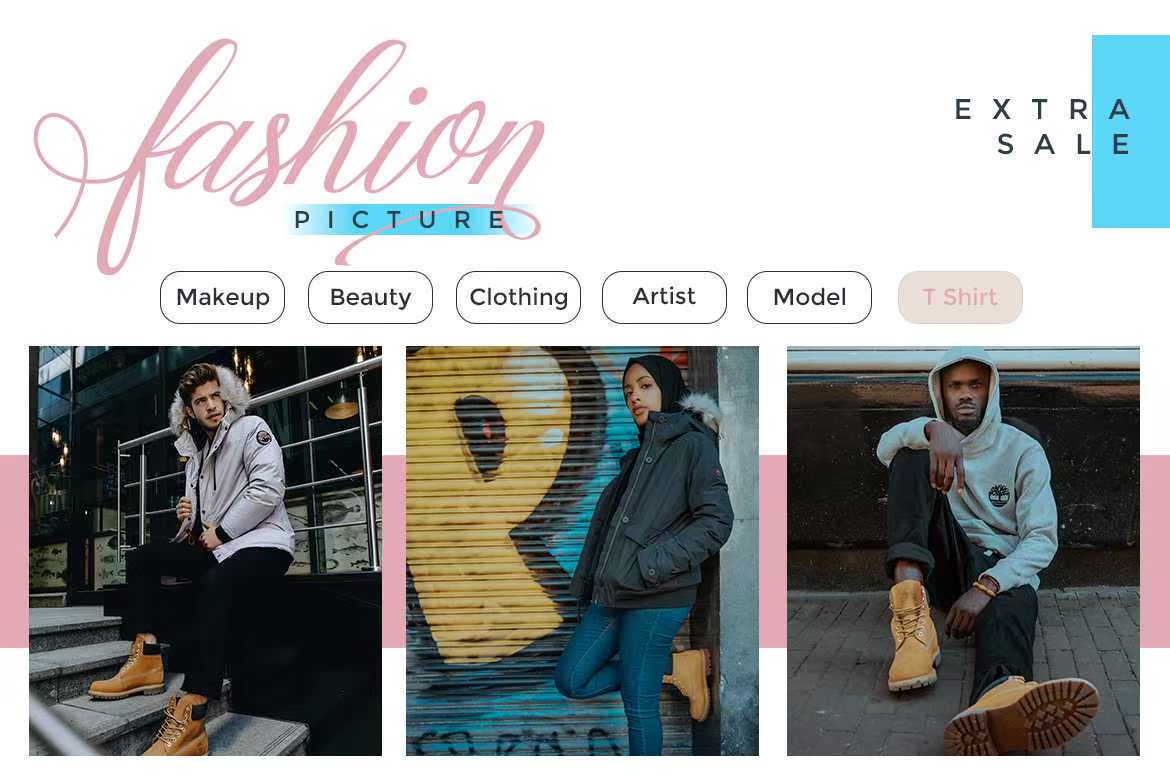
Mottingham Script是一种手写的英文铜版书法字体,从铜版到当代字体,具有鲜明的基线、经典和优雅的触感。可用于各种用途。例如标题、签名、徽标、婚礼宣传、t恤、信头、标牌、标签、新闻、海报、,badgesetc.MottinghamScript是一种手写的英文铜版书法字体,从铜版到带有基线、经典和优雅触感的即时字体相结合。可用于各种用途。如标题、签名、徽标、婚礼宣传、t恤、信头、标牌、标签、新闻、海报、徽章等。